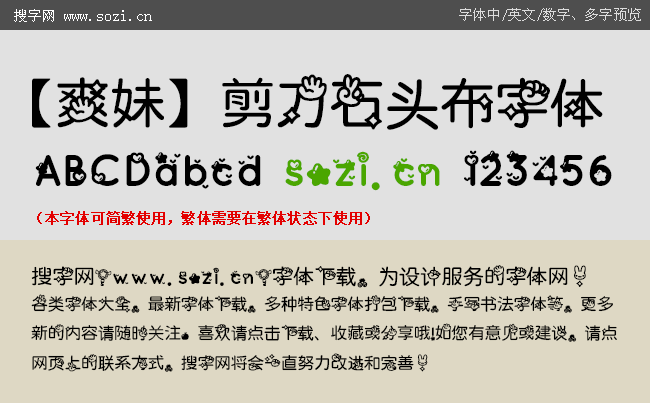
剪刀石頭布字體
搜字網(wǎng)給大家提供一款很可愛的手機(jī)中文字體下載。字體名叫剪刀石頭布字體,這款手機(jī)字體是以圓體字體為原形,筆畫間插入了可愛的剪刀石頭布手勢圖案。在具備圓字體清晰端正的風(fēng)格同時,卡通味也特別濃,是一款非常可愛的卡通字體,特別適合喜歡手機(jī)字體個性一些的朋友在手機(jī)上安裝使用。